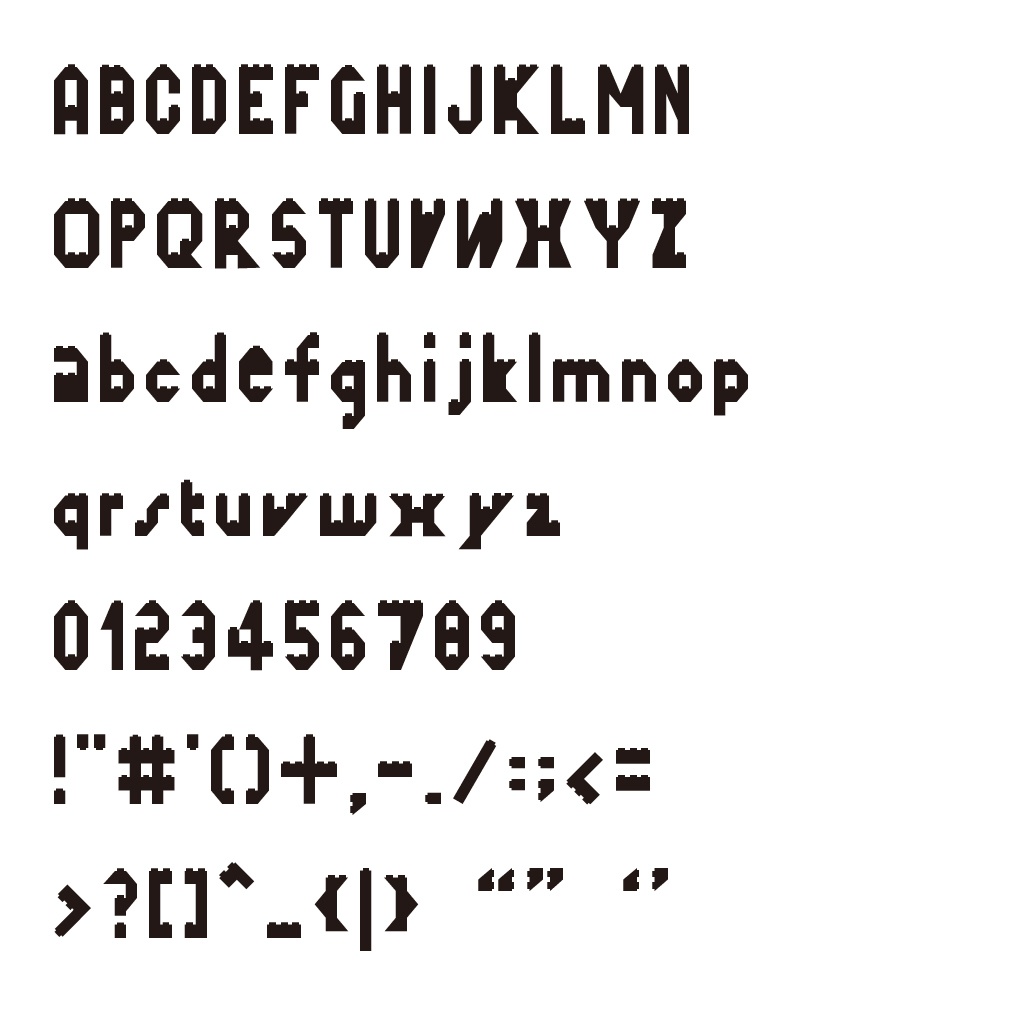
デジタルコンテンツ ブロック玩具フォント
組み立てブロックを組み合わせて作った文字をイメージした英語フォントです。 英語アルファベットの大文字と数字、記号のフォントを作成しました。 WindowsやMacで使用できるOpenTypeフォントです。 【収録文字】 英大文字 ABCDEFGHIJKLMNOPQRSTUVWXYZ 英小文字 abcdefghijklmnopqrstuvwxyz 数字 0123456789 記号 !"#'()^+,-./:;<=>?[]^_{|}“”‘’ 【データ内容・使用方法】 zipファイルをダウンロードして解凍してください。 OTFファイル pkblocktoy2-Regular.otf JPGファイル(文字表示の見本) font-sample.jpg テキストファイル readme.txt が収録されています。 pkblocktoy2-Regular.otf をインストールしてください。 【購入の際の注意点】 商用利用OKです。 使用した場合、ご一報いただけるとうれしいです。Twitterなどで紹介します。 フォントファイルの改変・再配布は禁止です。